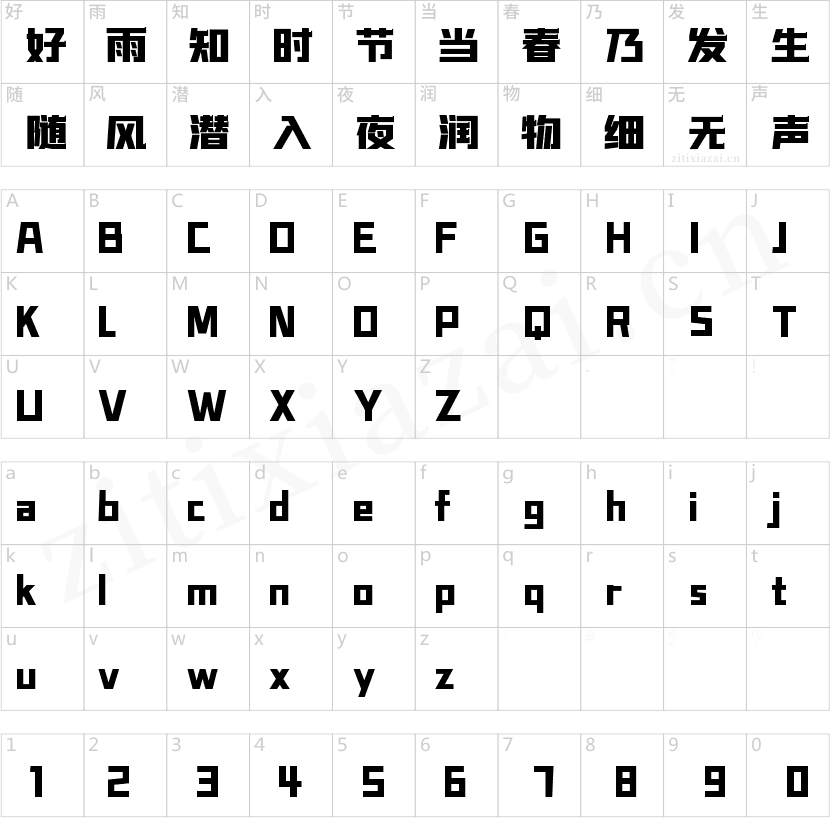
字魂正酷壮志黑
字魂正酷壮志黑是一款艺术字体,深受广大设计师的喜爱。
字体设计说明
字魂字体字魂正酷壮志黑字体是由字魂创意字库设计并生产的一款可商用的字体,被收录于字魂先锋系列。该字体支持GB-2312标准以及最新的字魂ZH7144标准,包含7144个中文、字母、符号和数字,字体类型偏向黑体,具有简约、时尚的风格,在市面上广泛用于视频综艺、活动促销、广告电商等场景。